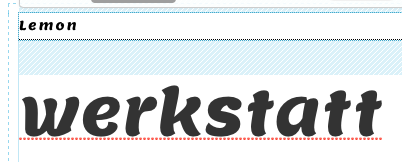
Ähnliche Schrift gesucht wie Lemon von google
Hallo, ich suche eine ähnliche Schrift, wie die Lemon Regular von google (https://www.google.com/fonts/specimen/Lemon).
Der grundlegende Stil von den Buchstaben soll gleich sein, aber dort wo die Ecken der Buchstaben wie z. B. beim "e" abgerundet sind, sollen diese eckig und kantig überall sein.
Wer kennt eine solche Schrift?
Okay – ein erster Annäherungsversuch ;-):
Kannst Dir ja mal die fetten Italics von z.B. ITC Chino, Auto, FF Amman Sans oder FF Tisa Sans ansehen und uns dann sagen was am ehesten in die gesuchte Richtung geht.
Hallo, erst mal danke für die Vorschläge. Leider ist aber die passende Schrift nicht dabei. Bei der Lemon sind halt manche Buchstaben charakteristisch wie z. B. das w. Im Prinzip soll es die gleiche Schrift sein aber überall wo runde Kanten sind müssten diese eckig sein. Ich glaub ich komm wohl um eine Bearbeitung der Schrift nicht drum rum. Die Schrift soll für ein Logo sein, in dem ein Teil "Werkstatt" ist, also die Buchstaben dann ähnlich einer Schraube mit einigen Ecken.
Also vielleicht gibt es ja ein Schrift, bei der ein "O" aussieht wie eine Schraube?
hmmh, sechseckig wie ein Schraubenkopf? oder irgendwie spiralförmig ... so aus dem Bauch raus mein ich, dass Du mit einem Auftrag an einen Grafiker ganz gut fahren könntest.
Ich würde die Schrift selber zeichnen. So etwas Spezielles, wie Du es im Sinn hast, wird schwerlich als Satzschrift aufzutreiben sein. Wenn Du Dir den gewünschten Text in der Lemon setzt und dann damit als Orientierung den neuen Schriftzug zeichnest, könnte das gut klappen.
Im Prinzip soll es die gleiche Schrift sein aber überall wo runde Kanten sind müssten diese eckig sein.
das möchte ich mal sehen wie das wirkt. das wird nicht funktionieren, darum gibt es so eine schrifte auch nicht.
es gibt fette script schriften die kantig sind aber das ist eher selten, ob das deinen vorstellungen entspricht weiß ich nicht aber schaue dir die mal an.
Möglicherweise ließe sich auch ein mehrkantiges, schraubenkopfartiges o gut in folgenden Kandidaten integrieren:
Außerdem man das mit dem Freefont London Olympics 2012 versuchen, wenn es scriptartig bleiben soll.
Könnte mir vorstellen, das auch Fraktur-Remakes brauchbar dafür wären. Müsste man mal testen.